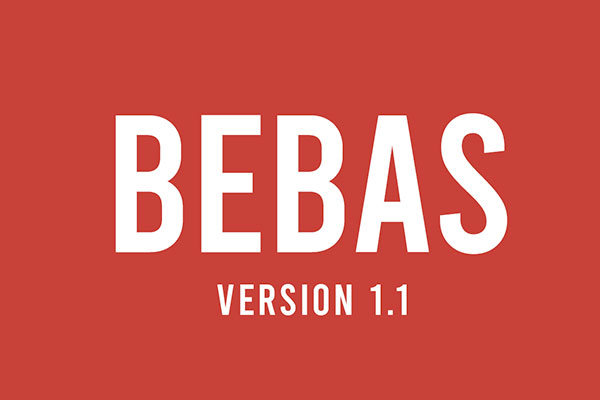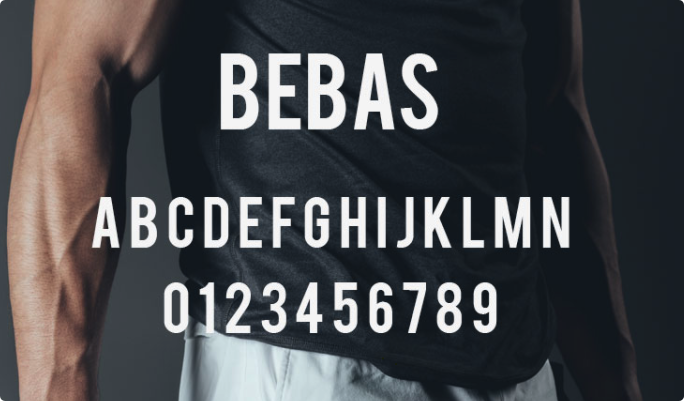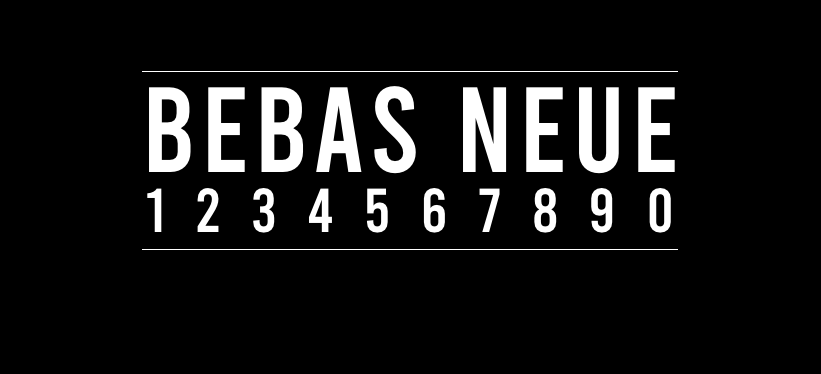
Bebas
Bebas字体介绍
Bebas是国外设计师Ryoichi Tsunekawa创作的一款字体,大家可能都用过一款名为DIN的字体,DIN字体非常优秀耐看,但是可惜的是DIN是一款商业字体,使用是需要授权的。而这款Bebas字体跟DIN就非常相似,可以作为DIN字体的替代字体,同样非常优秀。
Bebas字体应用示例